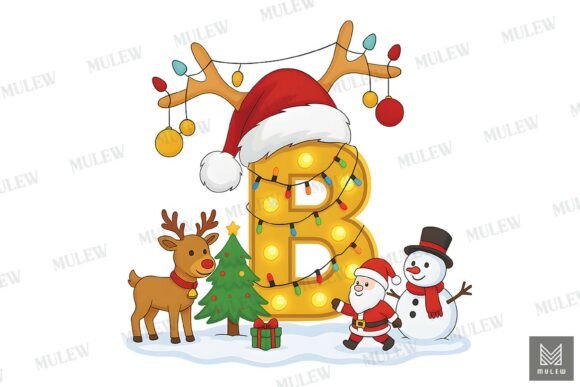
Christmas Letter B Sublimation PNG
การค้นหาองค์ประกอบการออกแบบที่เหมาะสมอาจเป็นเรื่องท้าทาย แต่ Christmas Letter B Sublimation PNG นำเสนอคอลเลกชันที่โดดเด่นซึ่งช่วยยกระดับงานของคุณได้ทันที
สร้างขึ้นอย่างแม่นยำ Christmas Letter B Sublimation PNG ให้เวกเตอร์ที่สะอาด พิมพ์ตัวอักษรที่ราบรื่น และใบอนุญาตเชิงพาณิชย์เพื่อความสบายใจ
ไม่ว่าคุณจะสร้างผลิตภัณฑ์ POD (Print on Demand) คำเชิญงานแต่งงาน หรือกราฟิกโซเชียลมีเดีย Christmas Letter B Sublimation PNG ก็เหมาะสมอย่างยิ่ง